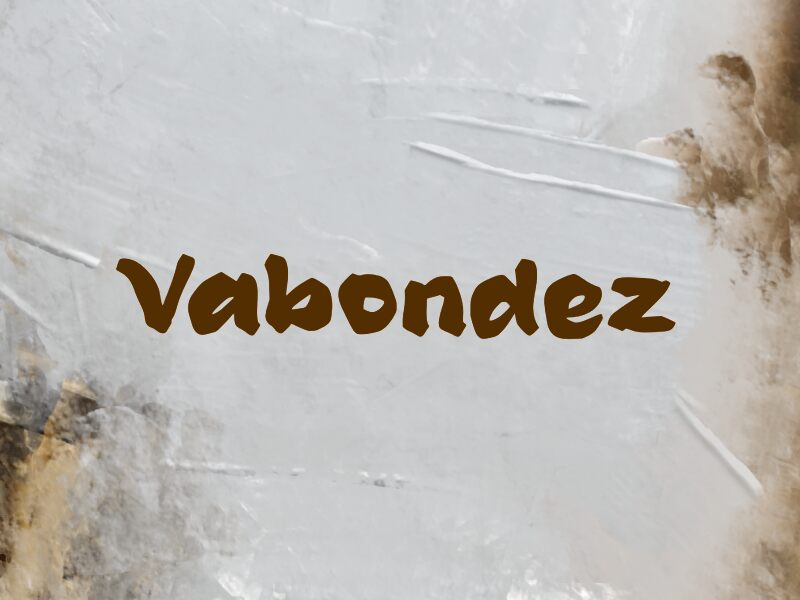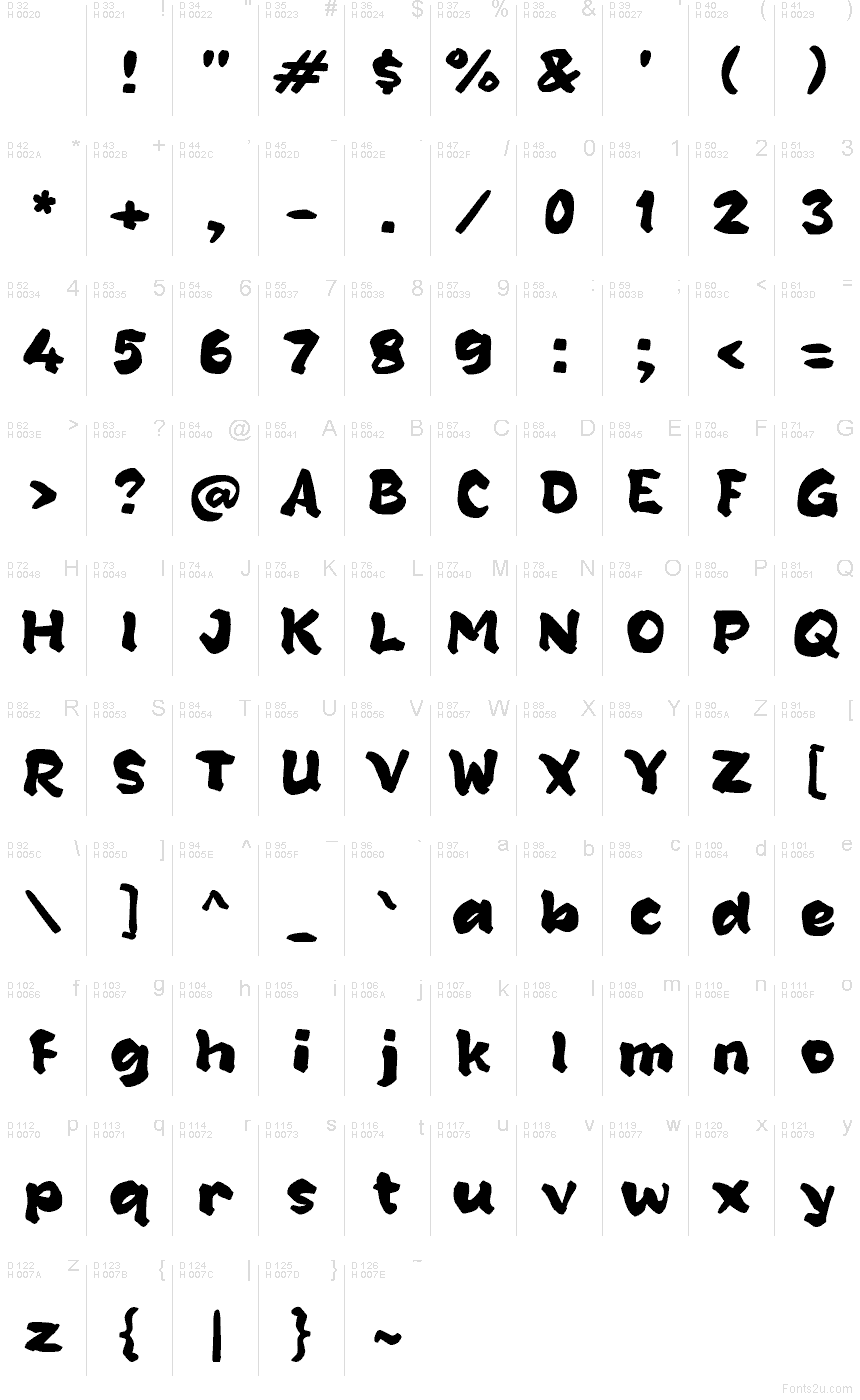
Vabondez od Wep to darmowy font typu brush o luźnym charakterze ręcznie malowanych napisów ulicznych. Jego litery są grube, surowe i lekko obdrapane, z ciężkimi krzywiznami, ciasnymi łączeniami i nierównymi krawędziami, które utrzymują żywy, nieuładzony rytm.
Dzięki temu to naturalny wybór na plakaty, oprawę graficzną muzyki, branding skate czy surf, okładki zinów i plansze tytułowe, gdzie liczy się szybkość i ludzki pierwiastek, a nie perfekcyjne wygładzenie. Jako darmowy font, Vabondez najlepiej sprawdza się w krótkich, wyrazistych formatach, takich jak logotypy, nagłówki czy monogramy, gdzie te masywne, pędzlowe kształty i nieregularne cięcia robią całą robotę.